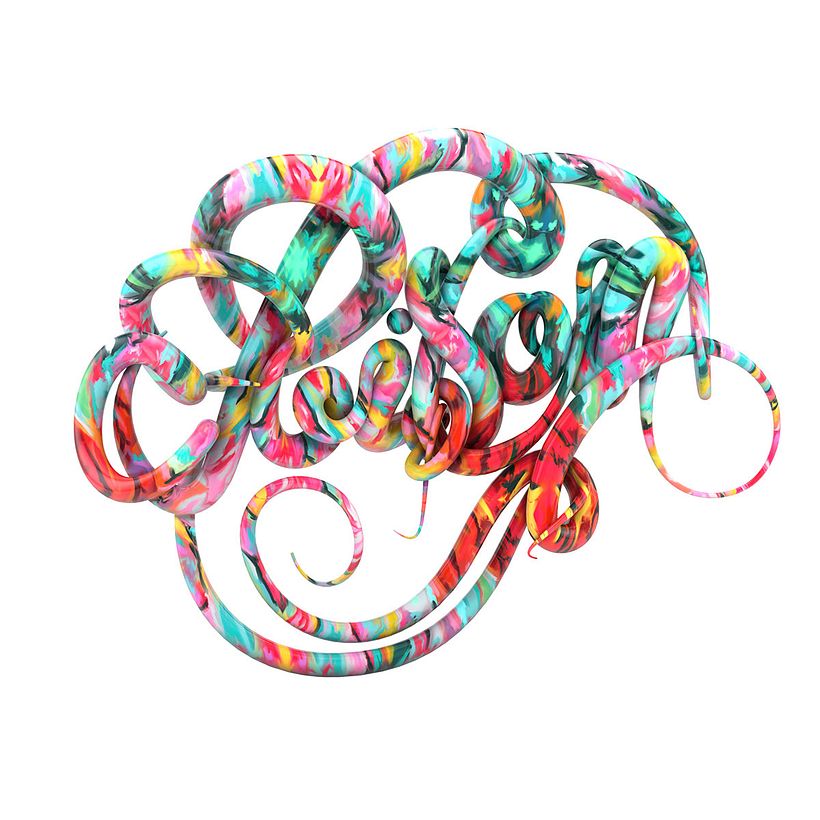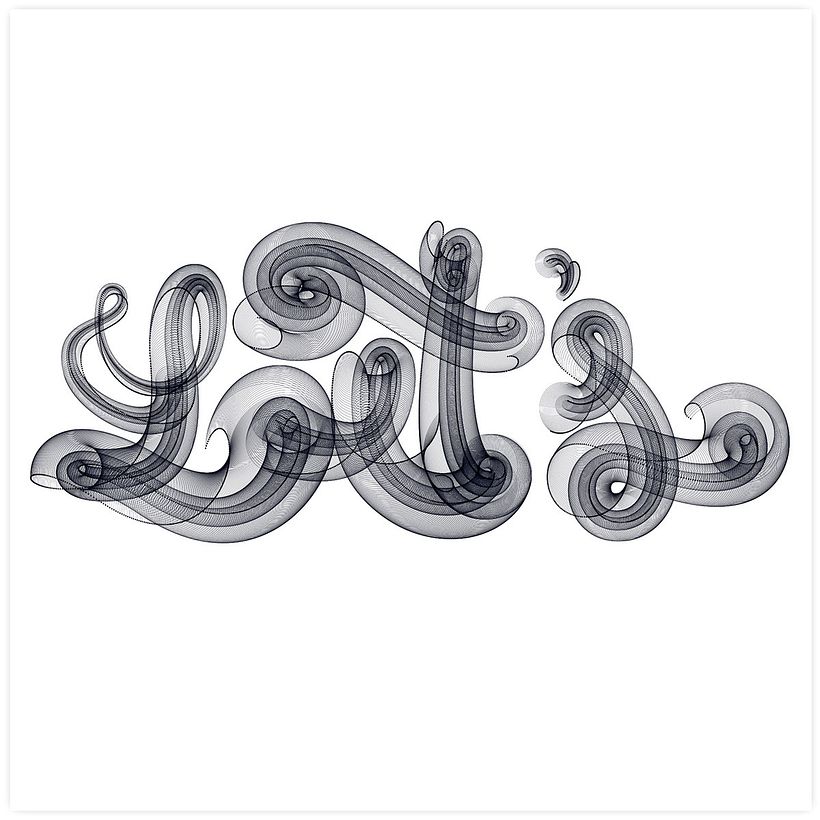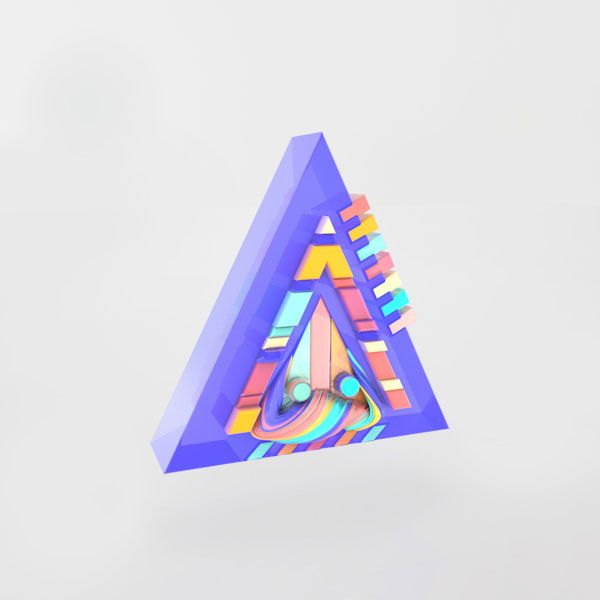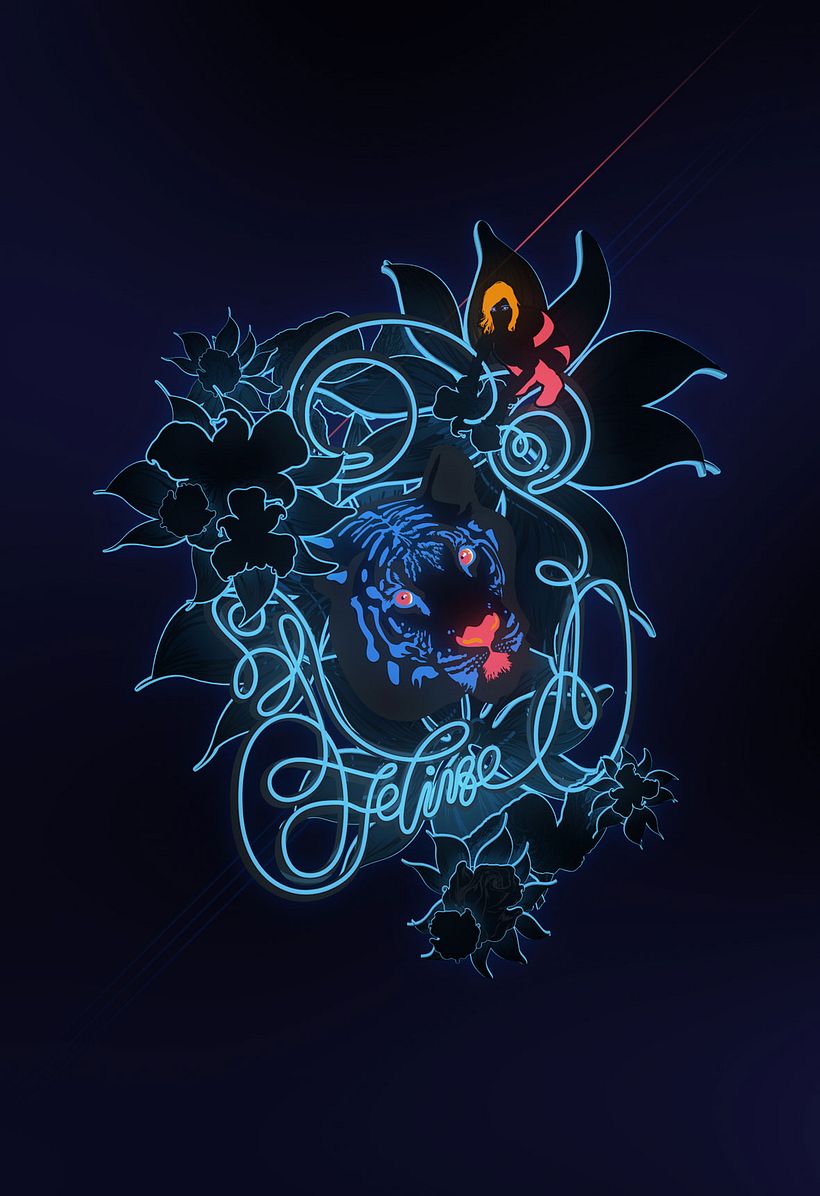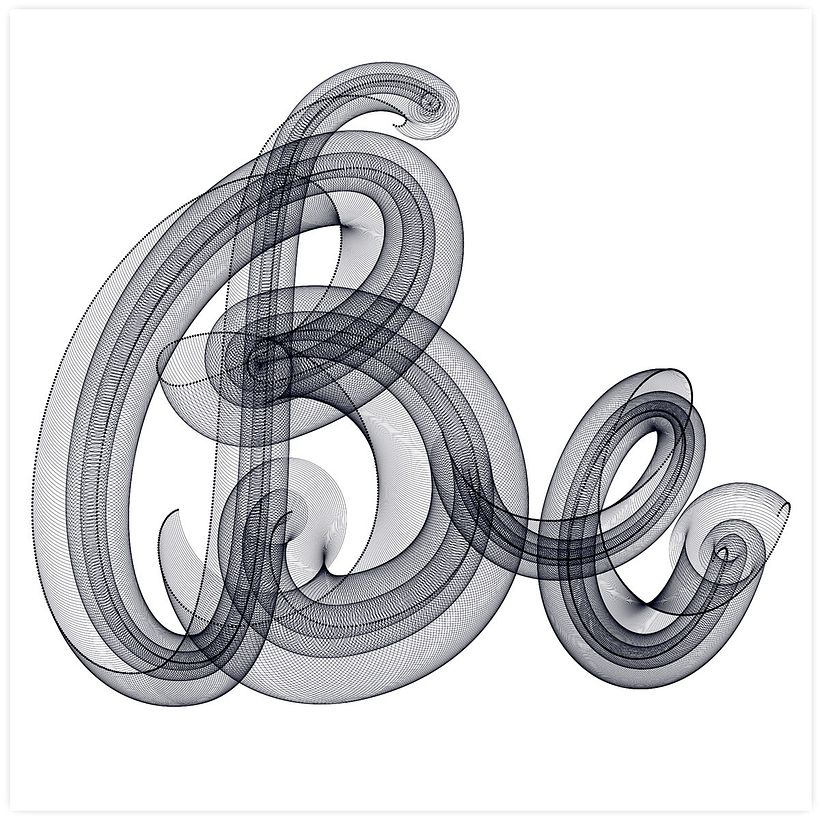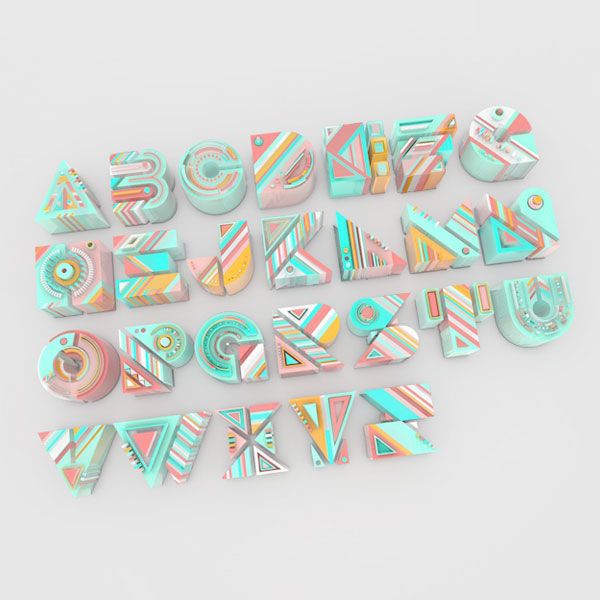
El arte de la tipografía de Ana Gómez Bernaus
El mundo de Ana Gómez Bernaus está lleno de letras. Su trabajo es un exhaustivo estudio tipográfico desde un punto de vista creativo y puramente visual.
Esta barcelonesa afincada en Estados Unidos comenzó a diseñar tipografías incluso antes de saber que ese maravilloso mundo existía. Desde niña ha rellenado páginas y páginas con letras y adornos. Su ciudad natal le sirvió de inspiración para sus primeros trabajos; tras mudarse a Nueva York y posteriormente a Los Ángeles, su estilo ha evolucionado hacia unas líneas más puras en el que la técnica experimental es la protagonista.
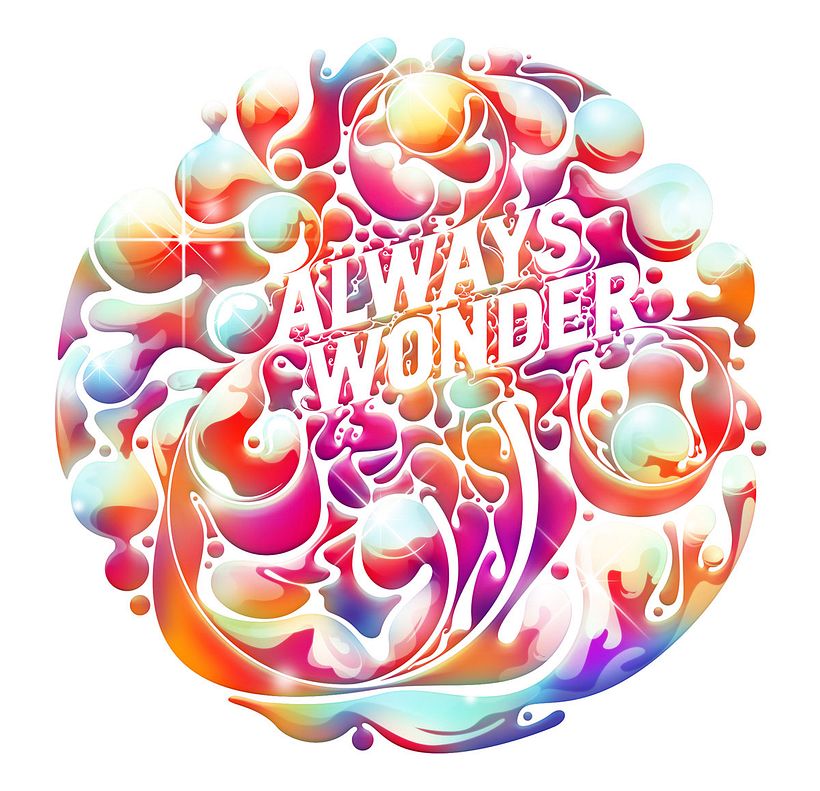
Los colores y las formas fluidas predominan en la obra de Ana Gómez, que ya ha trabajado para marcas como Nike, Converse, Trident, David & Goliath o JWT.
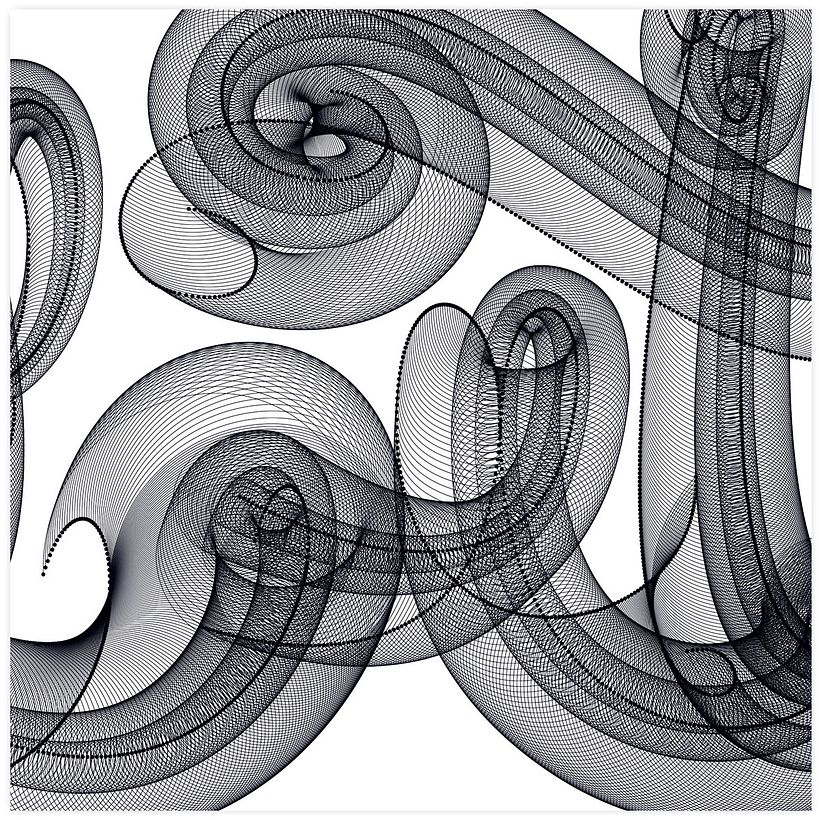
La geometría y el color son elementos con gran presencia en sus lettering, aunque no duda en experimentar con diferentes texturas y elementos orgánicos que, en muchas ocasiones, suponen un soplo de aire fresco y una llamada de atención a un mundo que, muchas veces, no recibe el interés que merece.
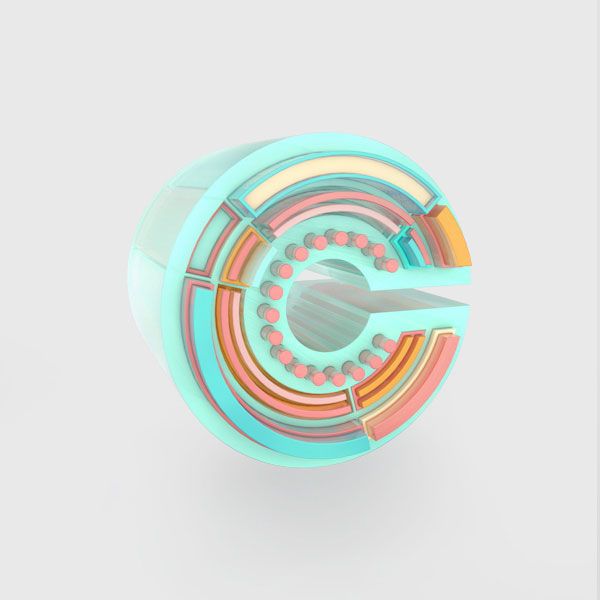
Sus diseños le han valido numerosos premios de vigencia internacional como SOTA & TypeCon 2016, Lürzer's Archive o Type Directors Club.